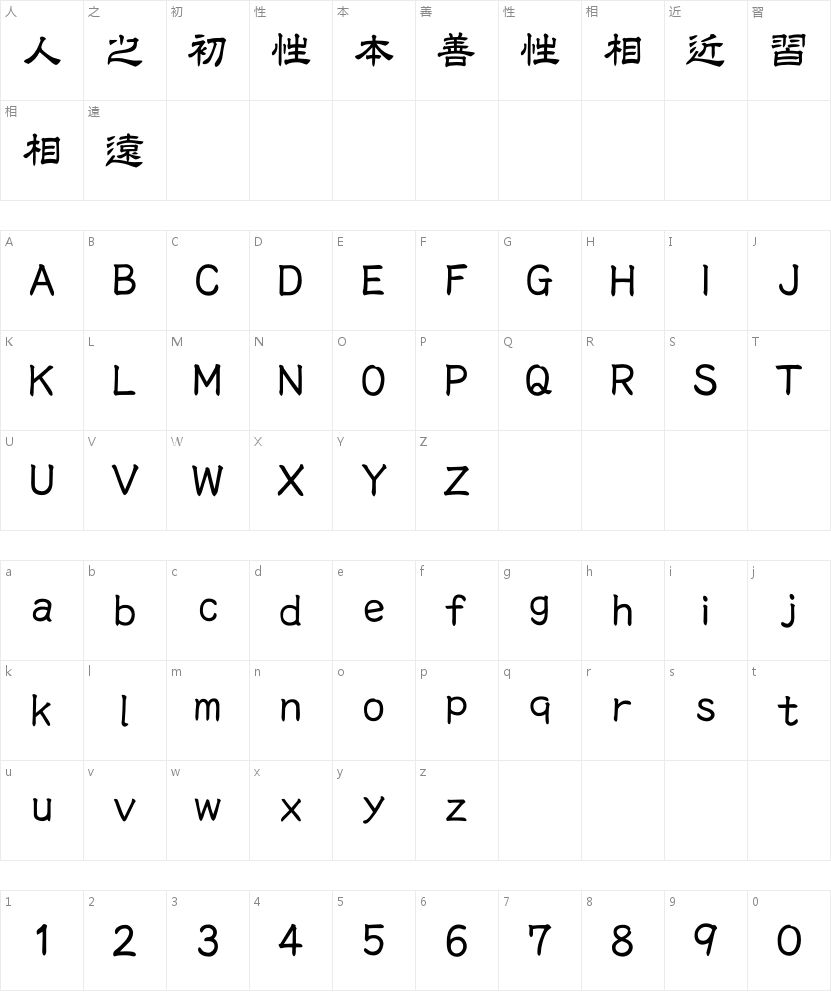
? HOT-白舟太隷書 Std B 是一種繁體中文字體,它是由日本知名字體設計師白舟太隷(Hiroshi Takahashi)設計的。這款字體以漢字為基礎,結合了日本傳統的書法風格,融合了日本古典文字的特色,形成了獨特的繁體中文字體。白舟太隷書 Std B 字體的字形設計簡潔大方,適用於中文排版,也可以用於日文文字的排版。內容介紹
HOT-白舟太隷書 Std B是一款非常不錯的手寫藝術字體,具有很好的視覺感,適合於文化類的宣傳設計、商業類品牌的廣告和產品包裝設計以及個性化文字排版等較多場景。